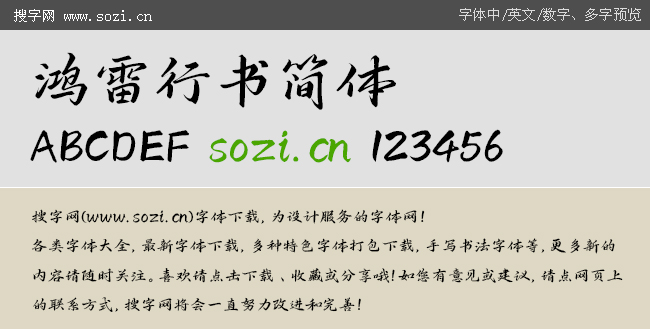
鴻雷行書(shū)簡(jiǎn)體
搜字網(wǎng)給大家提供一款鴻雷行書(shū)簡(jiǎn)體中文字體下載,鴻雷行書(shū)簡(jiǎn)體是國(guó)內(nèi)知名字體設(shè)計(jì)師殷鴻雷創(chuàng)作推出的第二款免費(fèi)商用書(shū)法字體。鴻雷行書(shū)簡(jiǎn)體字體筆鋒流暢行云流水,字形舒展有型。該字體依舊全渠道免費(fèi)商用。